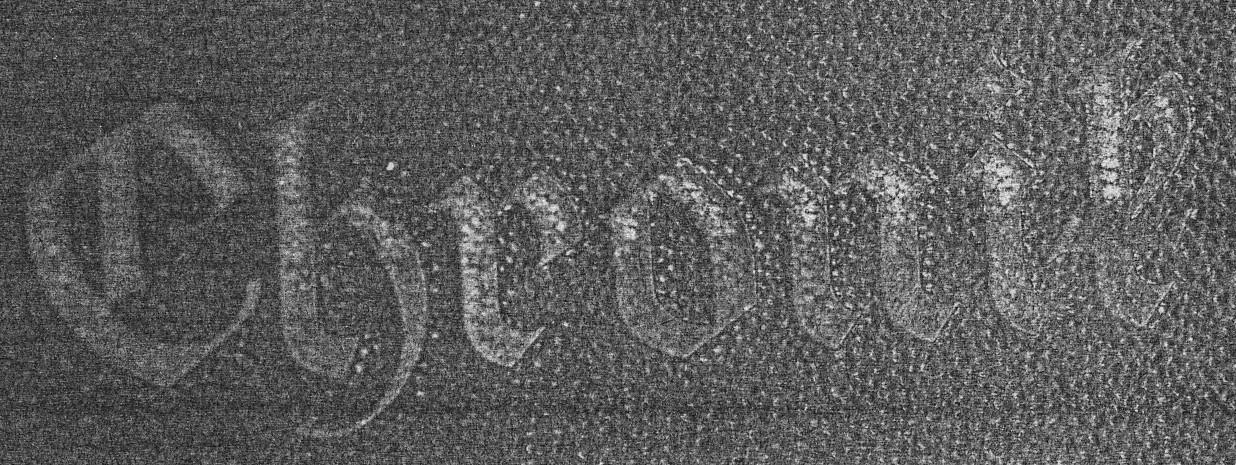
Ich suche eine Frakturschrift (Chronik-Einband)
ich suche eine Frakturschrift wie im Bild, ich hatte schon an Koch-Fraktur gedacht, aber da passt das kleine "k" nicht.
Entstehung so ca. im zweiten Welkrieg. Eingestanzt in einen Ledereinband.
Wen möglich suche ich es als Schriftart für einen Nachdruck.